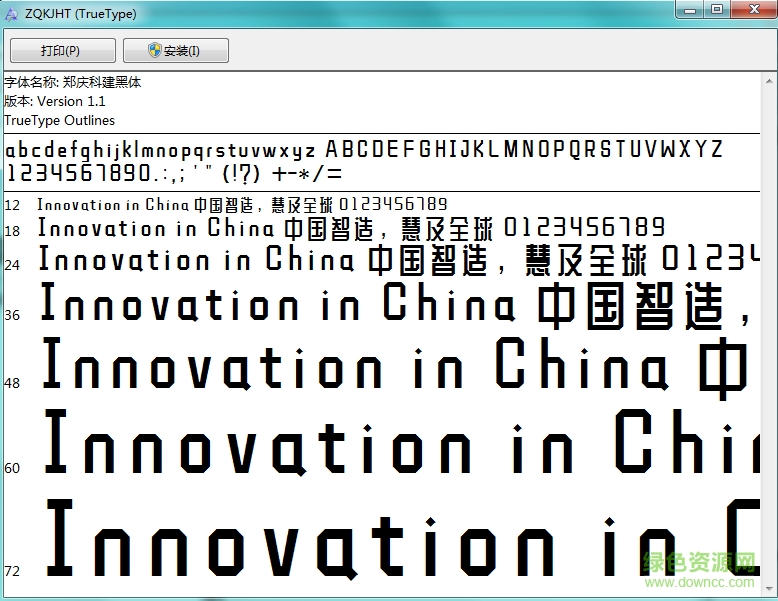
郑庆科建黑体是一款非商用的中文字体,字体有着极规整的四方形装,在部分笔画处又有着三角形的缺口,很有几何的美感,喜欢的朋友来绿色资源网免费下载吧!
建黑体由郑庆科所创,字体完整不缺字,支持繁简体输入,端正大气的造型很容易获得设计师的好感,广泛应用于平面设计、海报设计、LOGO设计等领域。
自2013年7月到2016年2月,终于把建黑体6763个汉字补全(GB2312标准),拖了很久,说真的,很累,很枯燥。